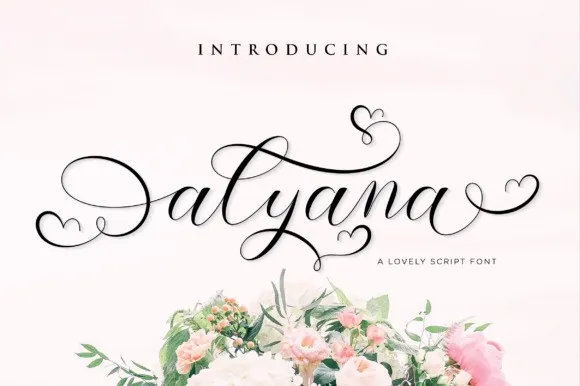
A Alyana Font é uma proposta moderna para designers que buscam uma solução que combine elegância com simplicidade. Inspirada na tipografia contemporânea, essa fonte traz sua própria assinatura ao design de cada projeto. Com um olhar moderno e sofisticado, ela oferece a capacidade única de adicionar um toque personalizado à sua arte digital. Ideal para quem busca uma combinação perfeita entre funcionalidade e estilo, a Alyana Font é a escolha certa se deseja destacar seus projetos com um touch único e atraente. A partir da 99designs, essa fonte oferece aos designers uma opção versátil e elegante para personalizar suas criações de forma única.